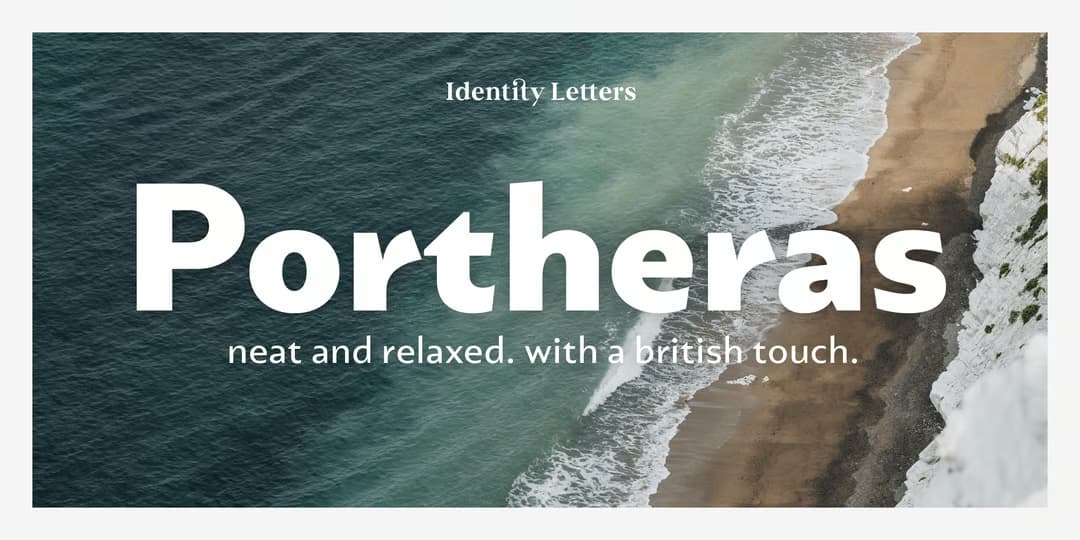
Portheras
クリーンでカジュアルなヒューマニストサンセリフ。手書きのニュアンスが多分に含まれ、柔らかい印象がありながら野暮ったくはなく、大変すっきりしていて読みやすい書体。イタリックはオブリークとの中間的なスタイルだが、こちらはより手書き風味がある。英国風味を意識しており、カジュアルでありながらも小さめのxハイトがエレガントさを醸し出している。「シルクのブラウスにサンダル、バミューダパンツにネクタイを着こなせる」ようにデザインしたとのこと。おっしゃれ~(笑)。名前は英国コーンウォールにあるビーチの事だそう。8ウェイト。